現代標誌設計的最佳字體
已發表: 2022-04-29如果您需要為您的項目創建一個現代標誌,您應該特別注意您使用的排版。 這個小元素真的可以產生巨大的影響。
字體具有表達品牌概念的力量。 你想讓它簡單嗎? 官方的? 浪漫的? 現代顯示字體將幫助您達到預期的效果。
要為您的標誌設計找到合適的選項,您需要查看在線目錄。 找到能代表您的項目理念並傳達公司信息的東西。 以下是一些用於現代標誌設計的流行字體。
Andada Pro 字體
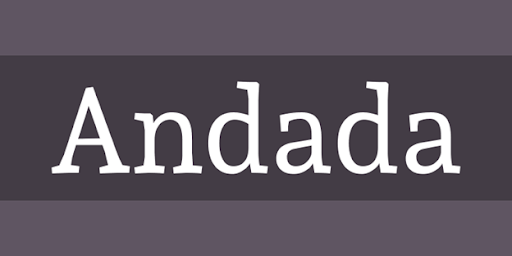
Andada Pro 是由 Huerta Tipografica Carolina Giovagnoli 開發的平板襯線字體。 它基於語言和排版之間的關係。
最適合: Andada Pro 最初是為在特定的雙語環境中使用而開發的,即西班牙語和瓜拉尼語。 現在它被用作不同類型文本的中等對比度類型。
最佳搭配: Roboto、Open Sans、Abel、Poppins 和 Advent Pro
山魯佐德新
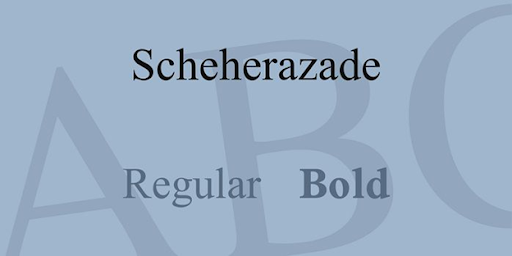
Scheherazade 是一種基於 Unicode 14.0 中阿拉伯文字字符的粗體字體。 它的名字來源於經典的一千零一夜故事。 它具有連接字形和附加連字或上下文替代項。
最適合: Scheherazade 可用於各種設備,例如 PC、Mac、Linux、iOS 和 Android。 這使其成為移動應用程序和計算機程序的完美字體。
最佳搭配: Roboto、Roboto Slab、Open Sans、Montserrat 和 Source Sans Pro
基督記憶顯示字體
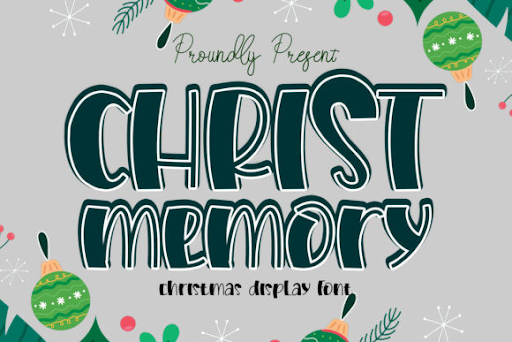
Christ Memory 是一種顯示字體,具有強大的字符和簡單的視覺概念。 它
結合了樂趣、獨特性和真實性,非常適合冬季和聖誕節項目。 基督記憶可以將任何創意變成傑出的!
最適用於: Christ Memory 字體適用於聖誕節模板/模型、T 卹、聖誕派對邀請函或明信片等產品設計。 該產品對您的創意設計非常有啟發性。
最佳搭配: Angels Fonts、Roboto、Georama 和 Raleway
Noto Sans Mono 字體
Noto Sans Mono 是屬於 Noto 系列的字體。 它用於 1,000 多種語言和 150 多種書寫系統。 由於視覺上簡約的設計,Noto Sans Mono 字體非常適合和諧、美觀和印刷準確的交流。 難怪它被廣泛用於編程代碼和其他需要固定寬度字體的用途。
最適用於: Noto Sans Mono 對不同的產品和項目非常有效——印刷和數字、私人和商業等等。
最佳搭配: Lato、Gilroy、Museo Slab、Montserrat、Noto Serif、Roboto 和 DIN
Mischa – 有趣的顯示字體
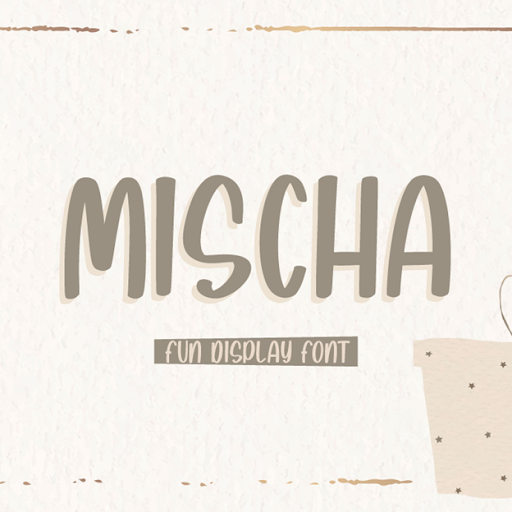
Mischa 是一種漂亮的顯示字體,它可以照亮任何項目。 很容易將此字體集成到任何設計概念中。 儘管視覺上很簡單,但它可以將您的項目創意變成真正的藝術品。
最適用於: Mischa 字體非常適合邀請函、明信片、標題菜單、顯示器、徽標、滑塊博客、燙印等。
最佳搭配: Work Sans、Roboto、Lato、Oswald 和 Georama
Bodoni Moda 字體
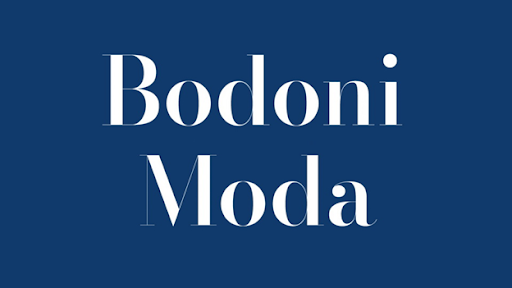
Bodoni Moda是數字時代時尚產品存在的一種戲劇性字體。 它是由 Giambattista Bodoni 創建的,他決定將粗細類型的特徵包裝到一個單獨的包中。
最適用於: Bodoni Moda 已被用於 Vogue 和 Calvin Klein 等知名標誌。 因此,對於一個在跑道上走極端的主流時尚品牌來說,這是一個很好的排版。
最佳搭配:蒙特塞拉特、Roboto、Roboto Slab、Open Sans 和 Poppins
Cormorant Garamond 字體
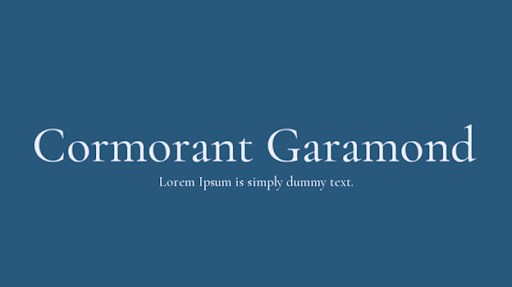
Garamond 是基於獨特字形的字體。 每個字母上的襯線似乎都有自己的個性,尤其是大寫“T”上的襯線。 襯線非常富有表現力,因此可以很容易地在有趣的環境中使用。 看看早期的 Apple 品牌。 平滑且均勻的字體允許這種字體用於復雜的設計——比如美國鷹標誌。
最適用於:由於外觀精緻,可用於嚴肅的設計。 這些可以是商業項目、醫療設施甚至大學課程的標誌。
最佳搭配: Roboto、Open Sans、Montserrat、Lato 和 Playfair Display
Abril Fatface 字體
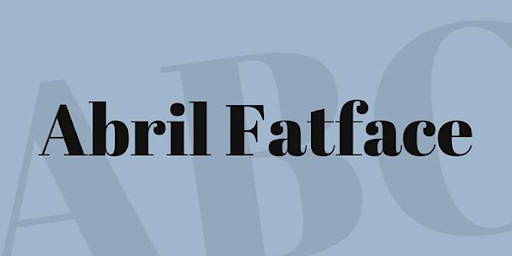
Abril Fatface 字體是對經典 Didone 風格的現代改造。 它具有一定的中立性,通過一定的技巧來吸引讀者的注意力。 Abril Fatface 具有引人注目的曲線、良好的色彩和高對比度,保證您的標誌設計具有優雅的外觀。
最適用於: Abril Fatface 主要以用於商業項目的定制設計而聞名。 它也是印刷和數字廣告活動的流行選擇。
最佳搭配: Open Sans、Roboto、Raleway、Playfair Display 和 Montserrat
Odibee Sans 字體
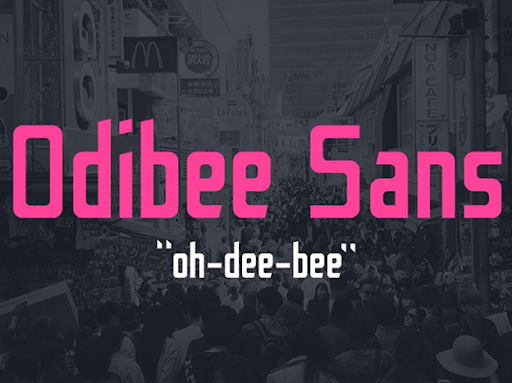
Odibee Sans 是由倫敦設計師 James Barnard 設計的一種顯示字體。 作者計劃開發獨特的一日構建 (ODB),但設法在 24 小時內創建了完整的字符集、數字和基本字形。 這個雄心勃勃且大膽的項目不言自明,與等寬字體和手寫字體完美搭配。
最適合: Odibee Sans 在雄心勃勃、有趣且引人入勝的標誌設計中看起來不錯。 這可以是私人時尚項目、商業計劃或公共社交活動。
最佳搭配: Roboto、Nunito、Open Sans、Nunito Sans 和 Roboto Condensed
為了實現一個靈巧優雅的標誌設計,你應該依靠簡單和
像上面提到的那些幾何字體。 既然您有很多選擇,您將能夠為您的徽標字體做出更好的決定。 憑藉敏銳的眼光,您一定會為您的項目找到完美的排版匹配。 如果您想更深入,請查看一些漂亮的印刷徽標以獲得更多靈感!